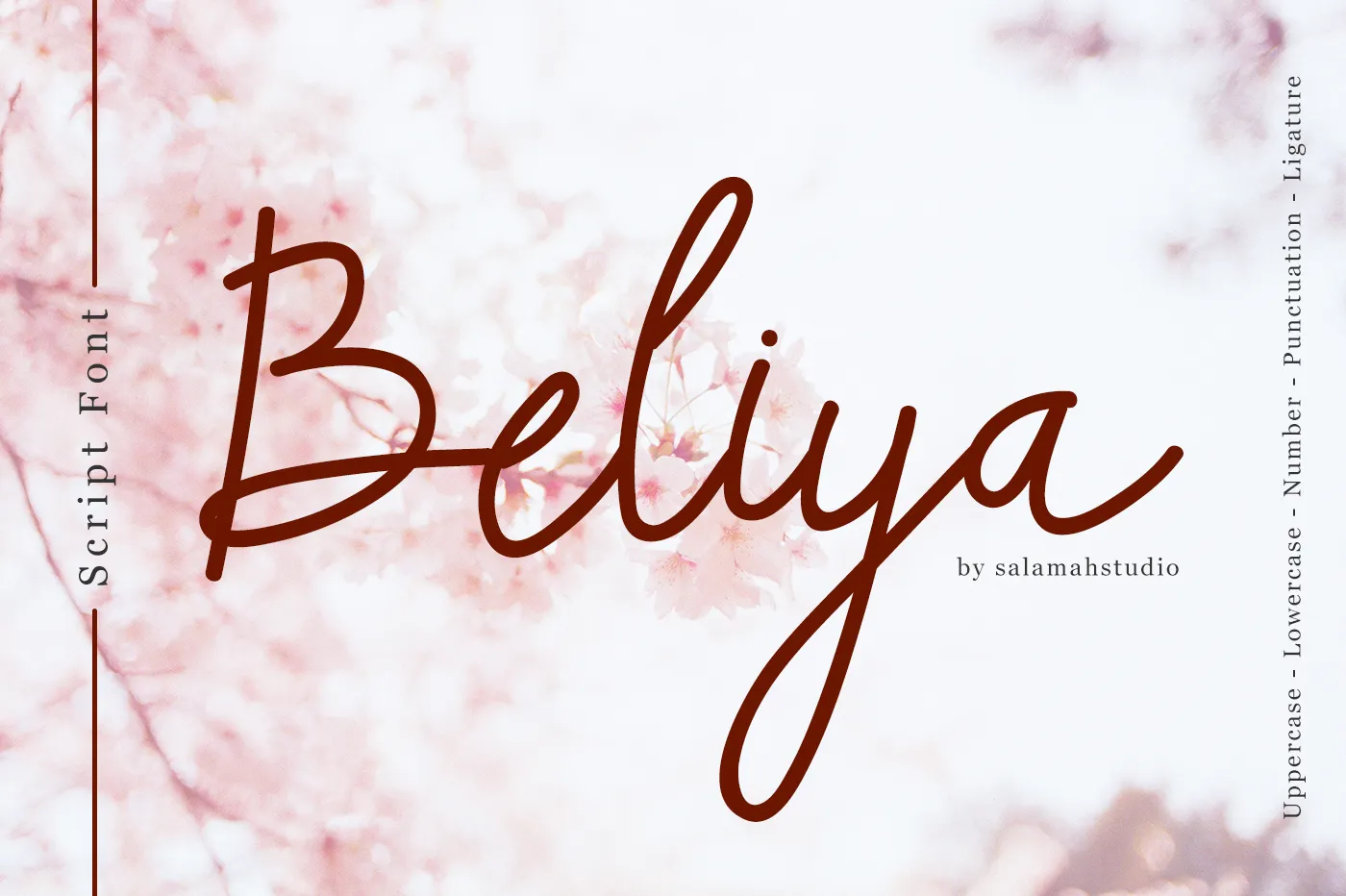
Beliya Script Font – Download Grátis
A “Beliya Script Font” é uma escolha perfeita para quem busca adicionar um toque moderno e elegante aos seus projetos. Esta letra script é leve e bem equilibrada, adaptada à categoria de Fonts Desenhadas à Mão com sua textura fluida e movimentos sutis, criando uma aparência única e sofisticada. Perfeita para se tornar a base de logo customizados ou assinaturas em t-shirts, ela é perfeitamente adequada para uso em avisos de casamento, cartazes de notícias, etiquetas, materiais promocionais, até mesmo como identificação nos próprios bastões. Essa fonte moderna e leve se adapta a uma variedade imensa de propósitos, tornando-a um recurso valioso para qualquer criador que deseja criar design único e atraente.